为理想踏出的每一步,
都值得用力一点!
痛哭后,
依旧是劲道又洒脱的少年。
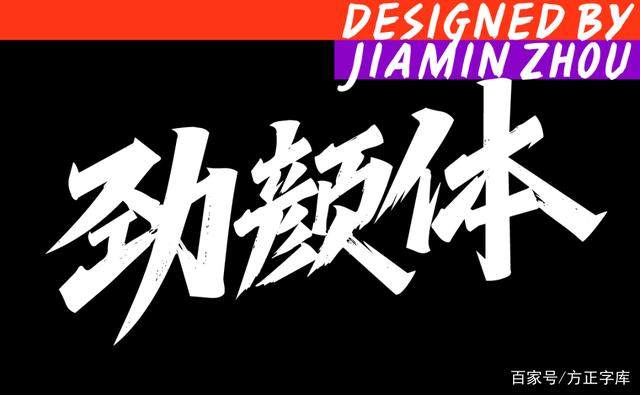
设计师周佳敏,一个特别有冲劲的白羊座女孩。字如其人,她的创意手写字体:劲颜体,也是一套特别有冲劲儿的字。
劲颜体,一开始命名为“景颜体”。后由于字体中宫饱满,笔形飒爽,转折潇洒利落,笔画间满是冲劲,所以改名“劲颜体”。
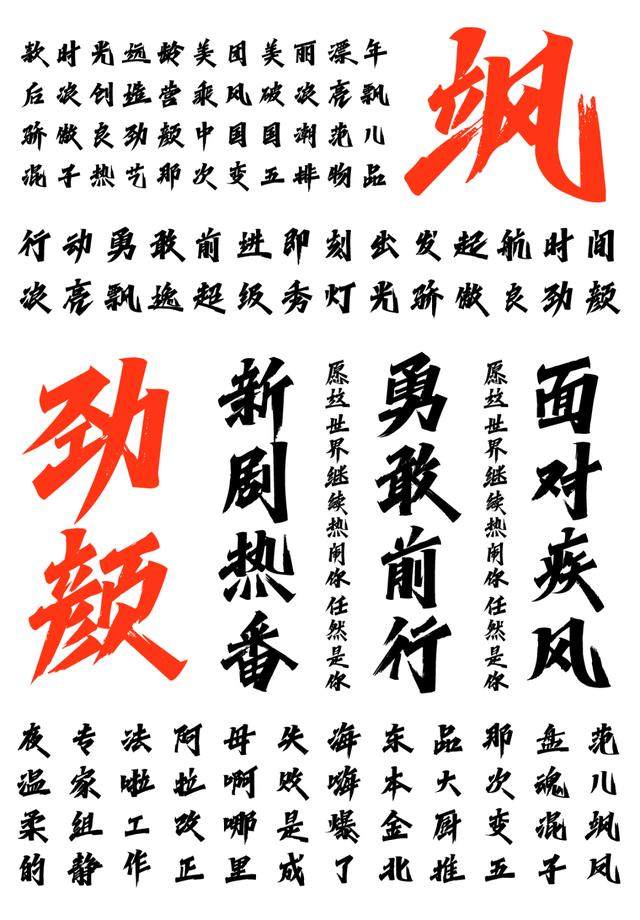
写这套字最难莫过于风格的统一。a4纸,每格8cm。在8cm的格子里,既要写出字体的力量感,还要保证字体大小、结构统一,不能出格。
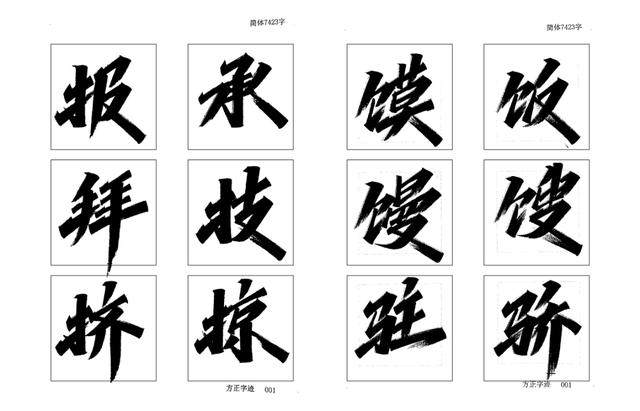
整个书写创作过程耗时近半年,用了136支秀丽笔。尤其是写到3000字左右的时候,由于书写工具的变换导致前后字型、字面大小、结构、布局不一致,不得不重写。
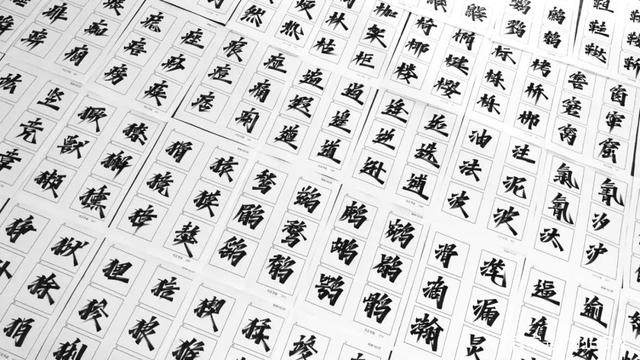
方正劲颜体是一款手写标题字体,整体结构饱满、重心平稳、趋势向上。笔画遒劲有力、稳中带速 、一气呵成,收笔带有飞白效果,大胆追求力量的释放,转折潇洒利落,风格极为强烈。
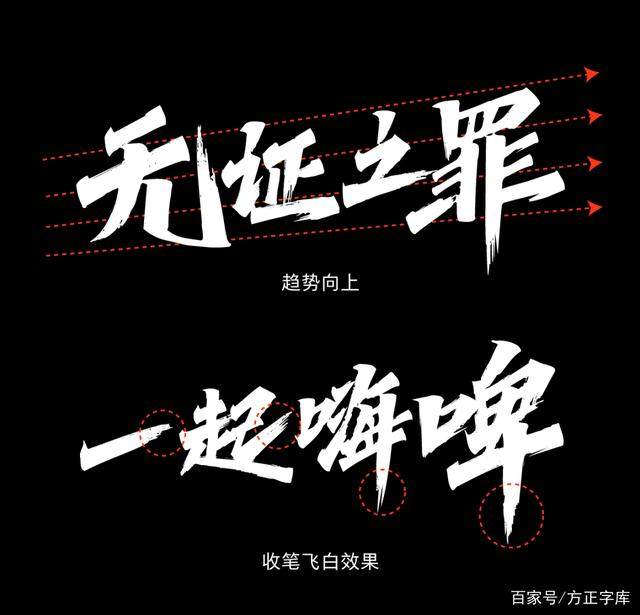
字体重心偏低显稳重,重心偏高显年轻挺拔。这套字体字形灵活舒展,重心略微偏高,给人年轻潮流的感觉。
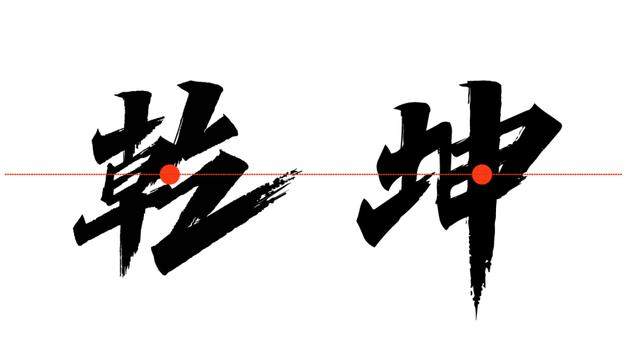
字势左收右放,呈现放射的形状,使得字体充满动感和活跃的氛围。
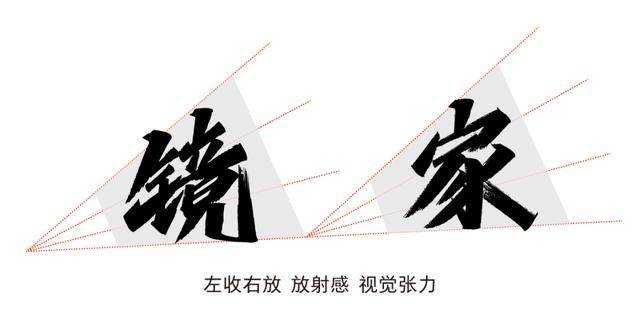
逆锋起笔,苍劲老辣,凸显字体的个性;行笔急速,笔锋峻利,增强字的力量;折笔肯定而凌厉,增强视觉冲击力;收笔干脆利落,保证字体的识别度。
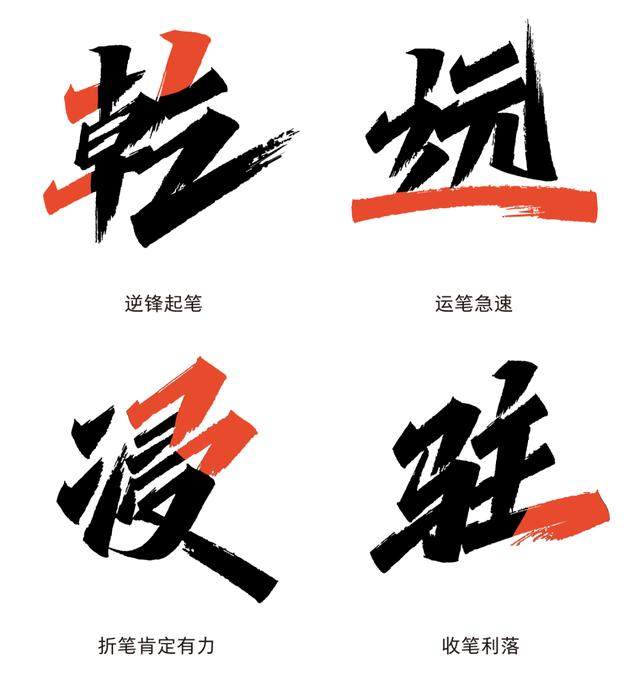
笔画方面,劲颜体的横画,粗壮豪放;竖画采用的是悬针竖,就像一把利剑;撇画做了灵动的变化,甩尾有力且丰富,空间感十足,急速而有力量。
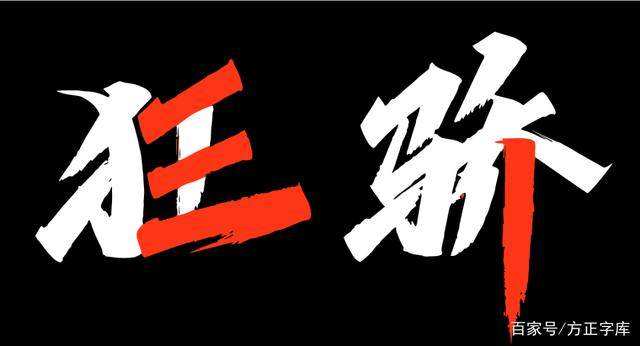
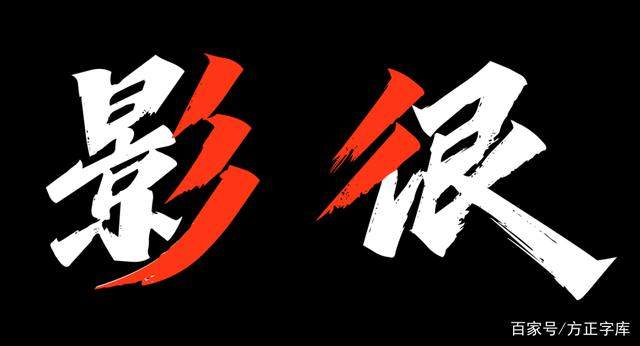
拥有以上设计特征的劲颜体,给人一种劲道飒爽、潇洒利落、富有张力的强烈感受。同时,它手写感强、个性十足、辨识度高,能够有效传达信息和表达情感。适用于各类时尚潮流、年轻活力的应用场景,在影视综艺、游戏动漫等方向也可以有不错的表现力。
字体设计师
周佳敏
方正字库字体设计师
微博设计美学博主、抖音人气创作者
代表作品:方正字迹-劲颜体
昵称周周,90后,开朗爱笑的白羊座,对自己够狠的“拼命三娘”。爱好写字、跑步、阅读、撸猫。大学专业为视觉传达,因在互联网公司的设计工作中大量接触字体,从而痴迷字体设计并最终成为了一名专职字体设计师。曾为歌手彭楚粤的新歌设计歌名,为小米、京东、苏宁等品牌提供字体设计服务。
工作之余坚持学习书法,大量创作手写作品,并尝试将书法与当下潮流文化以及商业元素相结合,逐渐形成自己的创作风格,个人首款创意书写字体——方正字迹-劲颜体于2020年7月开发完成。
劲道而不失严谨,
洒脱又不失凝重,
新生代设计师的创新之作,
你值得拥有!